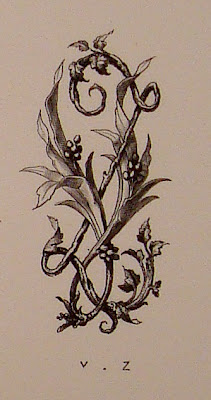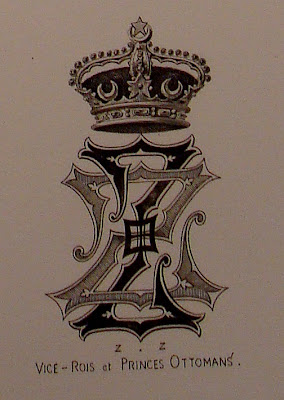
| Monograma de todo el ALFABETO- Demengeot, 1881 |
DEMENGEOT, Ch. "DICTIONNAIRE DE CHIFFRE-MONOGRAMMES DANS LES STYLESET RENAISSANCE ET COURONNES NOBILIAIRES UNIVERSELLES."
Paris: Demengeot- Juliot, 1881, 2 Volúmenes.
- Vol. I: Gran Folio (33x44), Una hoja con la primera pre-portada con título y dedicatoria del autor manuscrita a:Aglaïus Bouvenne, detrás un monograma, una hoja con un Heliograbado de Dujardin del retrato de Demengeot, una hoja en blanco, una hoja repitiendo la 1ª portada igual que el primer folio, una hoja con la portada a dos tintas, rojo y negro, tres hojas numeradas en romanos, 98 páginas de la primera parte, 116 páginas de la segunda parte, 1 hoja con la justificación de la tirada, una hoja en blanco.
- Vol. II: Gran Folio (33x 44), Atlas de láminas, la portada con el famoso Monograma de todo el alfabeto grabado por el autor y colección de 33 láminas con diferentes monogramas y coronas heráldicas.
Tirada solo de 200 ejemplares en gran folio y papel superior.
Sin duda es un libro en mayúsculas y el trabajo y diseño de los monogramas lo sitúan en la cumbre de esta especialidad.
En esta entrada pondré los monogramas y nombres que contienen las láminas:28, 29 y 30 de este libro, esto incluye las letras T, U , V, X , Y y Z con sus combinaciones con las letras letras del alfabeto, también incluye algunos nombre propios..
Esta será la última entrada dedicada al libro de Demengeot y con esta termino la serie de 10 entradas que han ocupado desde el mes pasado el espacio en Bibliotypes.
| Lámina nº 28 , Demengeot. 1881 |
| Lámina nº 29 - Demengeot, 1881 |
Lámina dedicada a monogramas al estilo antiguo: Edad Media y Renacimiento . (Lámina nº 30- Demengeot, 1881)
Letra T
|
| T-T |
|
| T-T |
|
| T-V |
|
| T-U |
|
| T-W |
|
| T-W |
|
| T-X |
|
| T-Y |
|
T-Z
|
| T-Z |
|
Monograma de THÉODORE Demengeot, 1881
|
Monograma de THÉODORE Demengeot, 1881 |
Letra U
|
| U-U |
|
| U-V |
|
| U-W |
|
| U-W |
|
| U-X |
|
| U-Y |
|
| U-Y |
|
| U-Z |
Letra V
|
| V-V |
|
| V-W |
|
V-X
|
| V-Y |
|
V-Y
|
| V-Z |
|
| Monograma de VIRGINIE |
Letra W
|
W-W
|
W-X
|
W-Z
|
| W-Z |
Letra X
|
| X-X |
|
| X-X |
|
| X-Y |
|
X- Z
|
Letra Y
|
Y-Y
|
| Y-Y |
|
| Y-Z |
Letra Z
|
| Z-Z |
|
| Z-Z |
Monogramas al estilo de la Edad Media y Renacimiento: Lámina 30
|
Monograma antiguo de A-G Demengeot, 1881
|
Monograma antiguo de A-G Demengeot, 1881 |
|
Monograma antiguo de S - F Demengeot, 1881 |
|
Monograma antiguo de S - F Demengeot, 1881
|
Monograma antiguo de ROSINE Demengeot, 1881 |
|
Monograma antiguo de de ROSINE Demengeot, 1881 |
|
Monograma antiguo de de O - LARRI Demengeot, 1881 |
|
Monograma antiguo de O - LARRI Demengeot, 1881 |
|
Monograma antiguo de VÍCTOR Demengeot, 1881 |
|
Monograma antiguo de VÍCTOR Demengeot, 1881 |